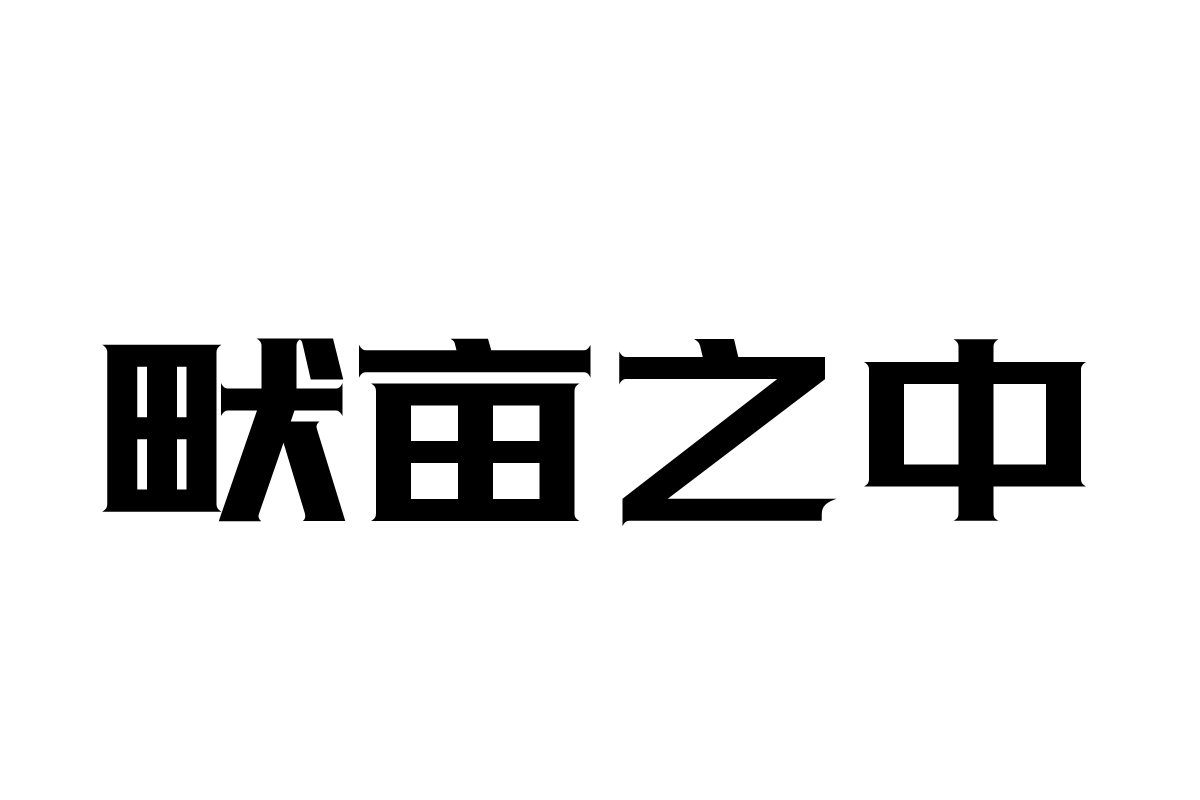
“三极光耀”简体字是一种具有独特美感的汉字字体,它以简洁、大方、易读为特点。这种字体采用了现代设计元素,线条流畅,结构紧凑,给人一种清新、自然的感觉。
在设计上,“三极光耀”简体字注重线条的粗细变化和空间的利用,使整个字体既有力度又不失优雅。同时,它还注重字形的平衡和对称性,使得整体看起来既和谐又富有动感。
这种字体适用于各种场合,如广告、海报、包装、书籍等,能够很好地传达出设计者想要表达的主题和情感。无论是用于商业还是艺术,“三极光耀”简体字都能展现出其独特的魅力。